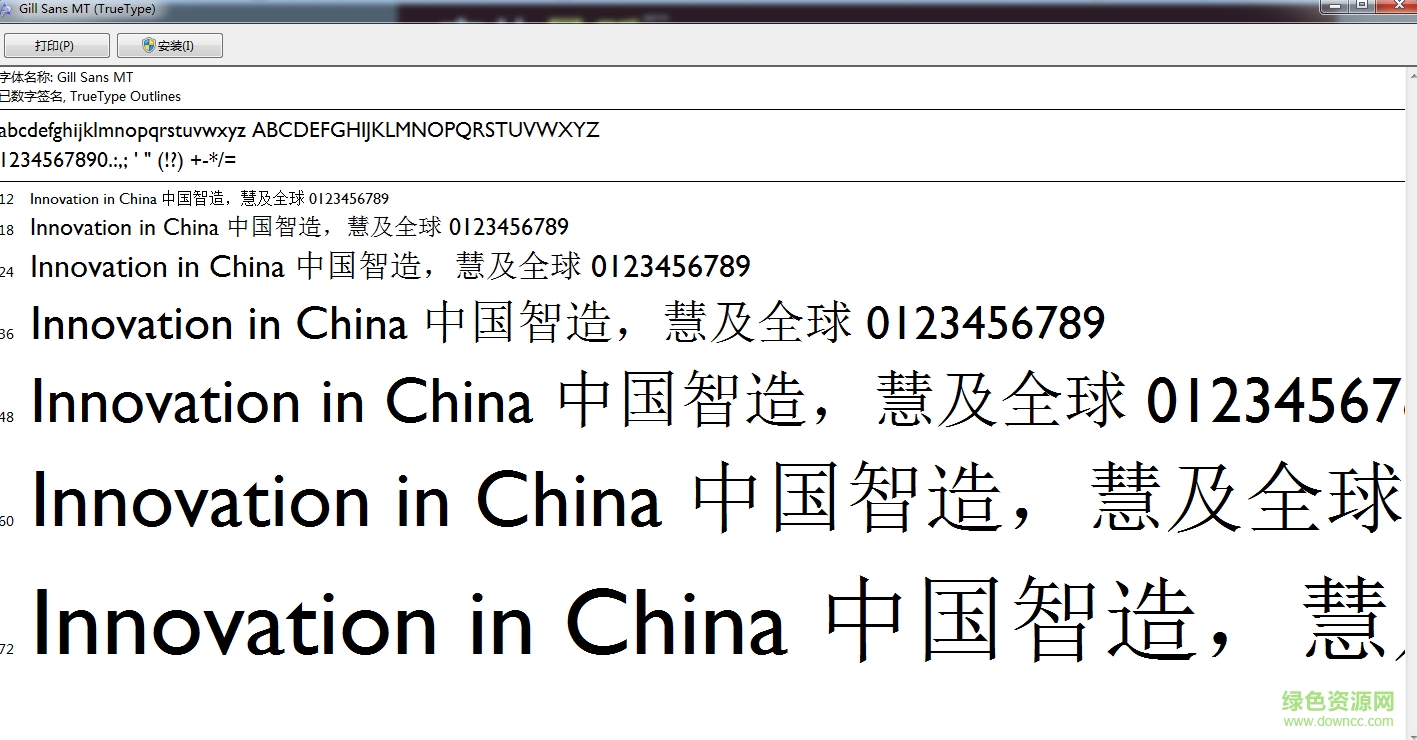
gill sans mt字體是一款可讀性極高的英文字體,字型飽滿,字體線條流暢,看上去明快大方,實用性強,打印效果也非常出色,歡迎大家在綠色資源網(wǎng)下載!
Gill Sans字體是Monotype公司1928年設(shè)計的一種字體,Gill Sans字體被指定為第28屆雅典奧運會官方打印字體,大概這種字體的設(shè)計師吉爾先生(Eric Gill)也預(yù)想不到,無論潮流如何變化,技術(shù)如何發(fā)展,他設(shè)計的字體會顯示出如此強大的生命力,而且Gill Sans字體還與奧運會的要求非常吻合。